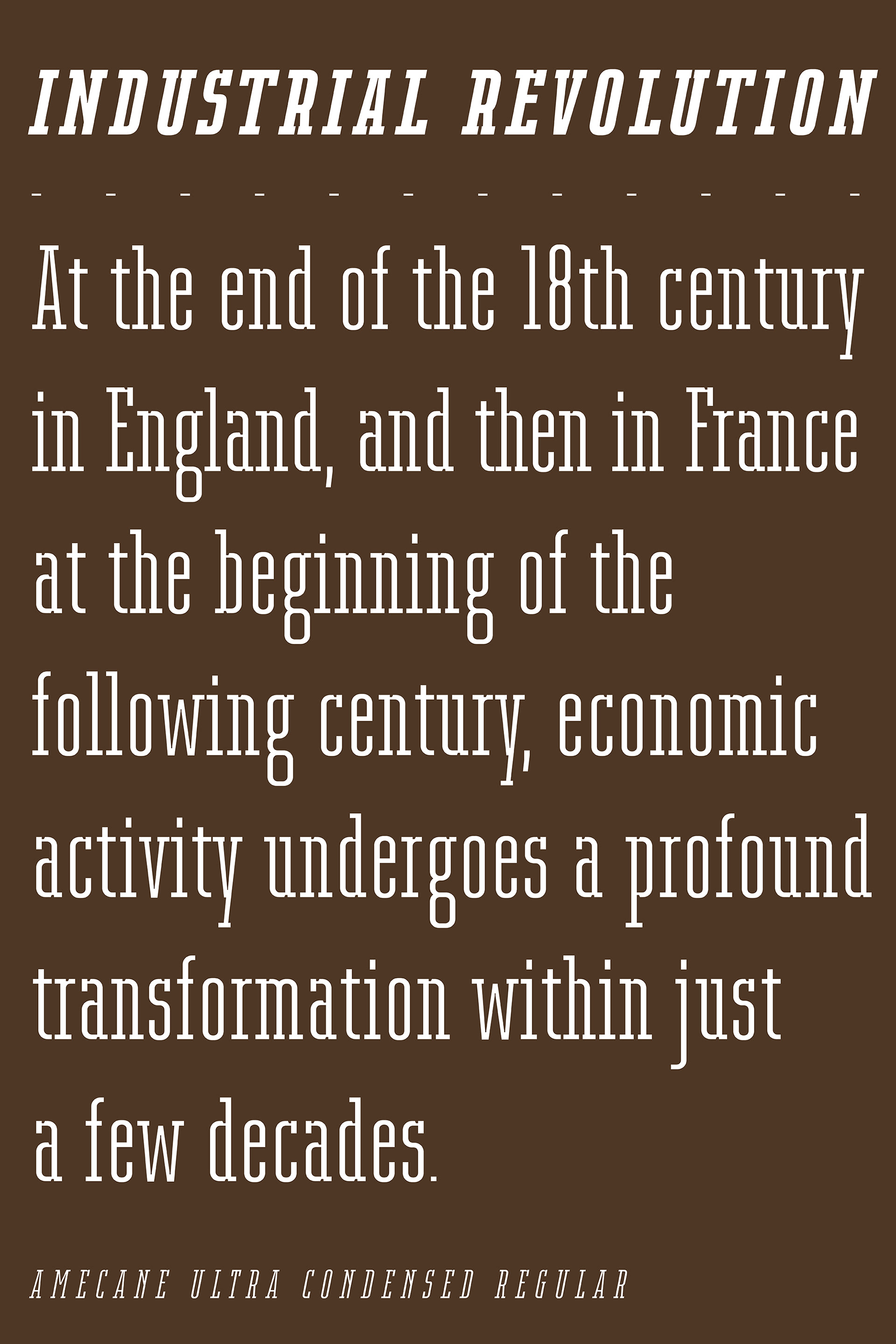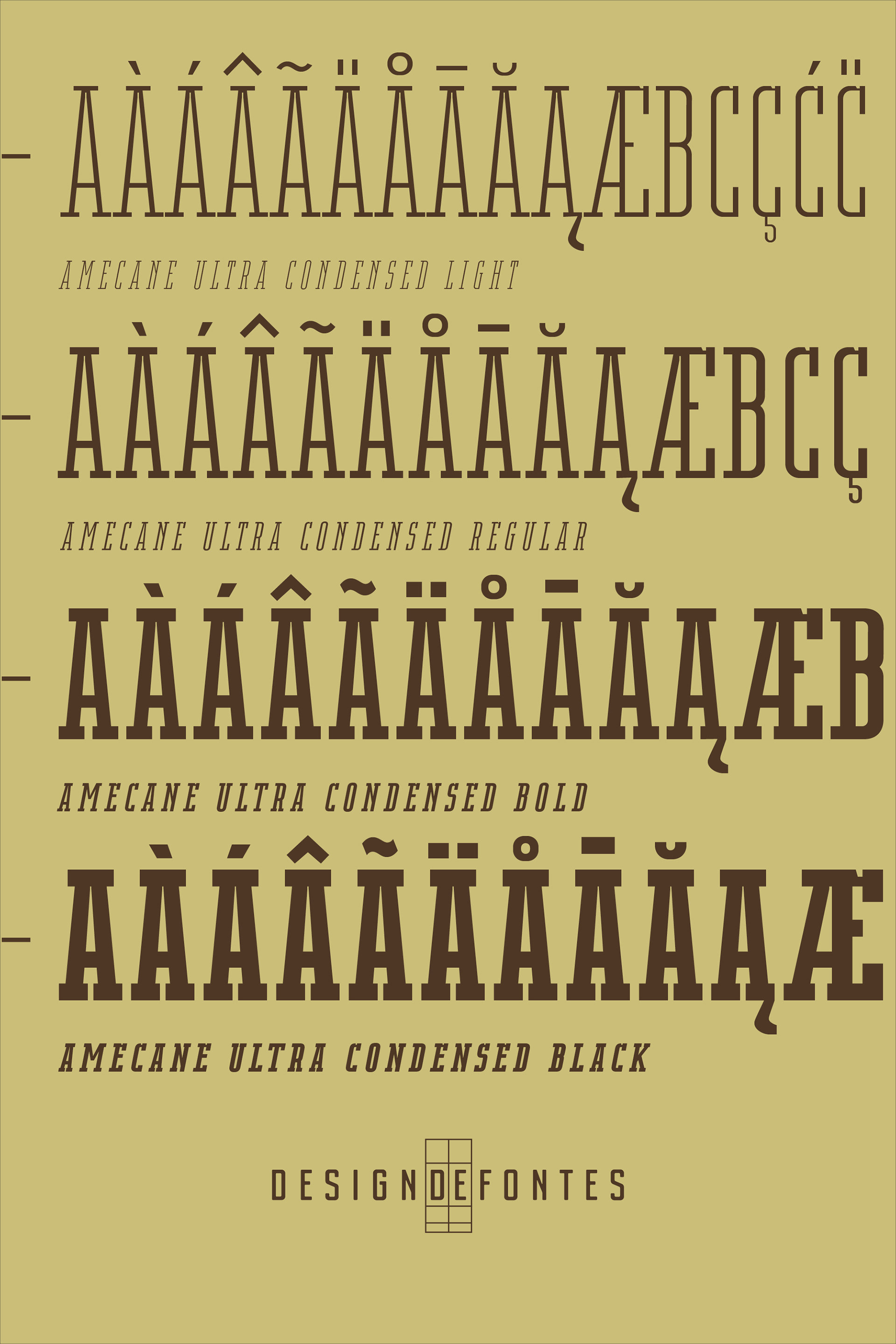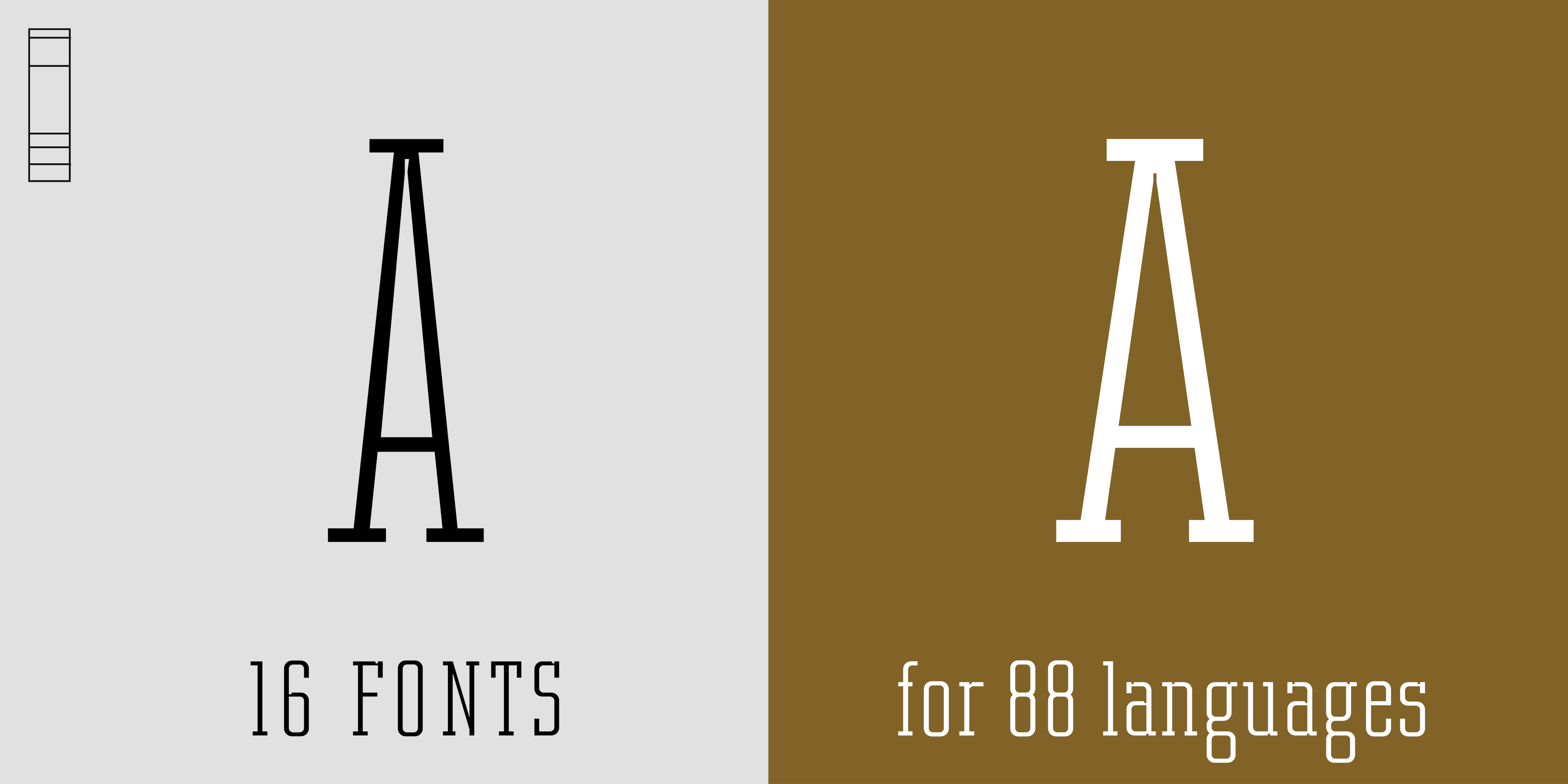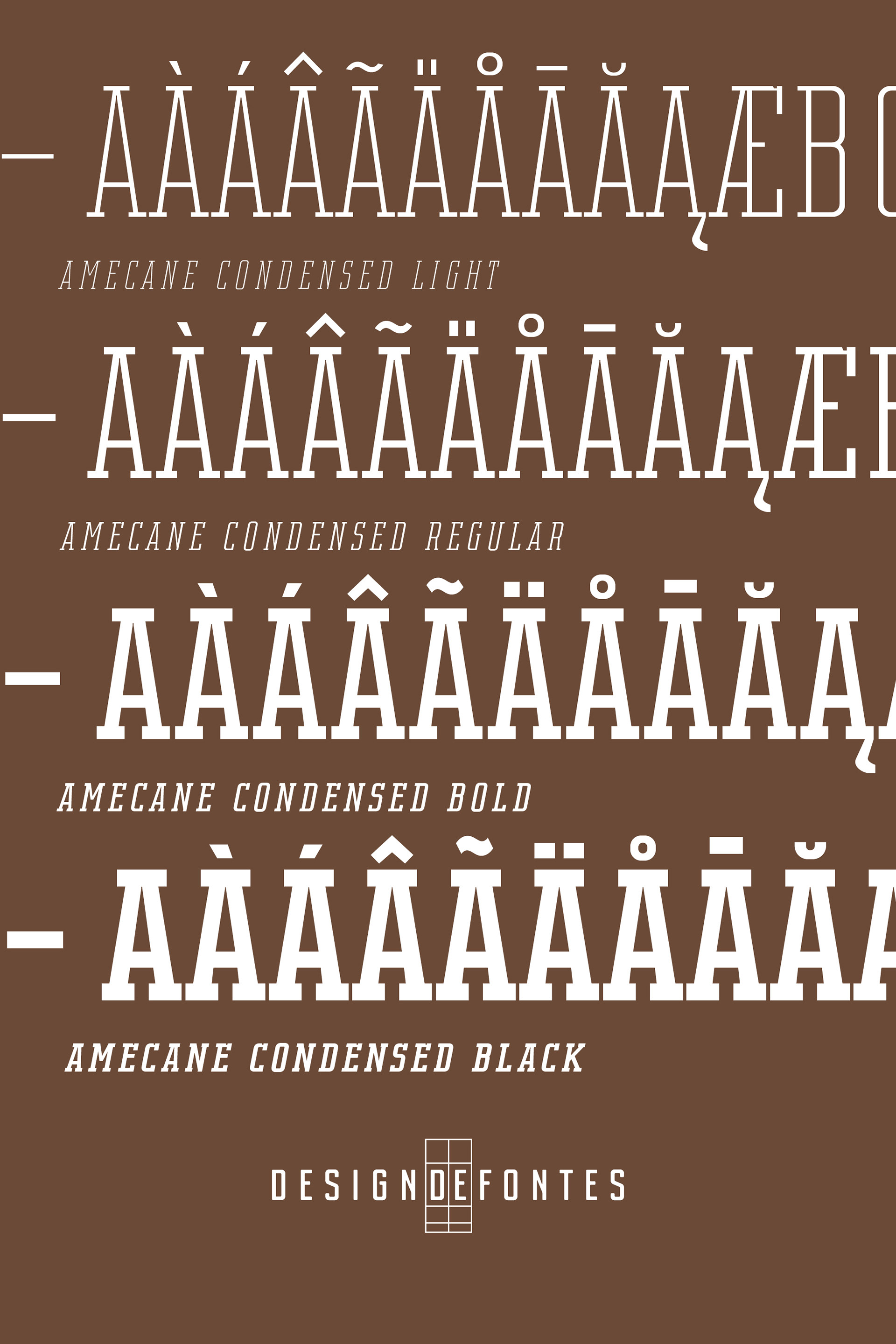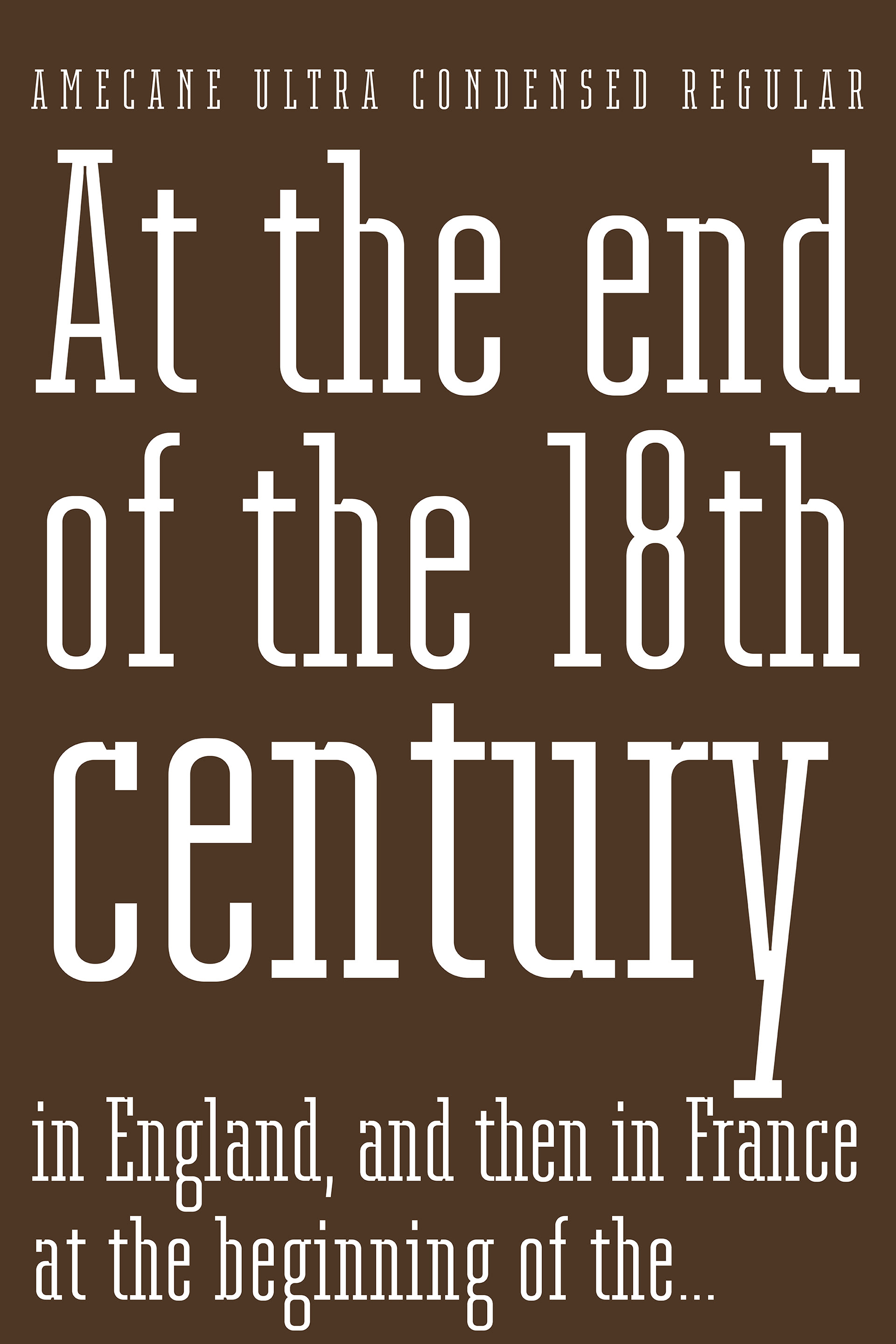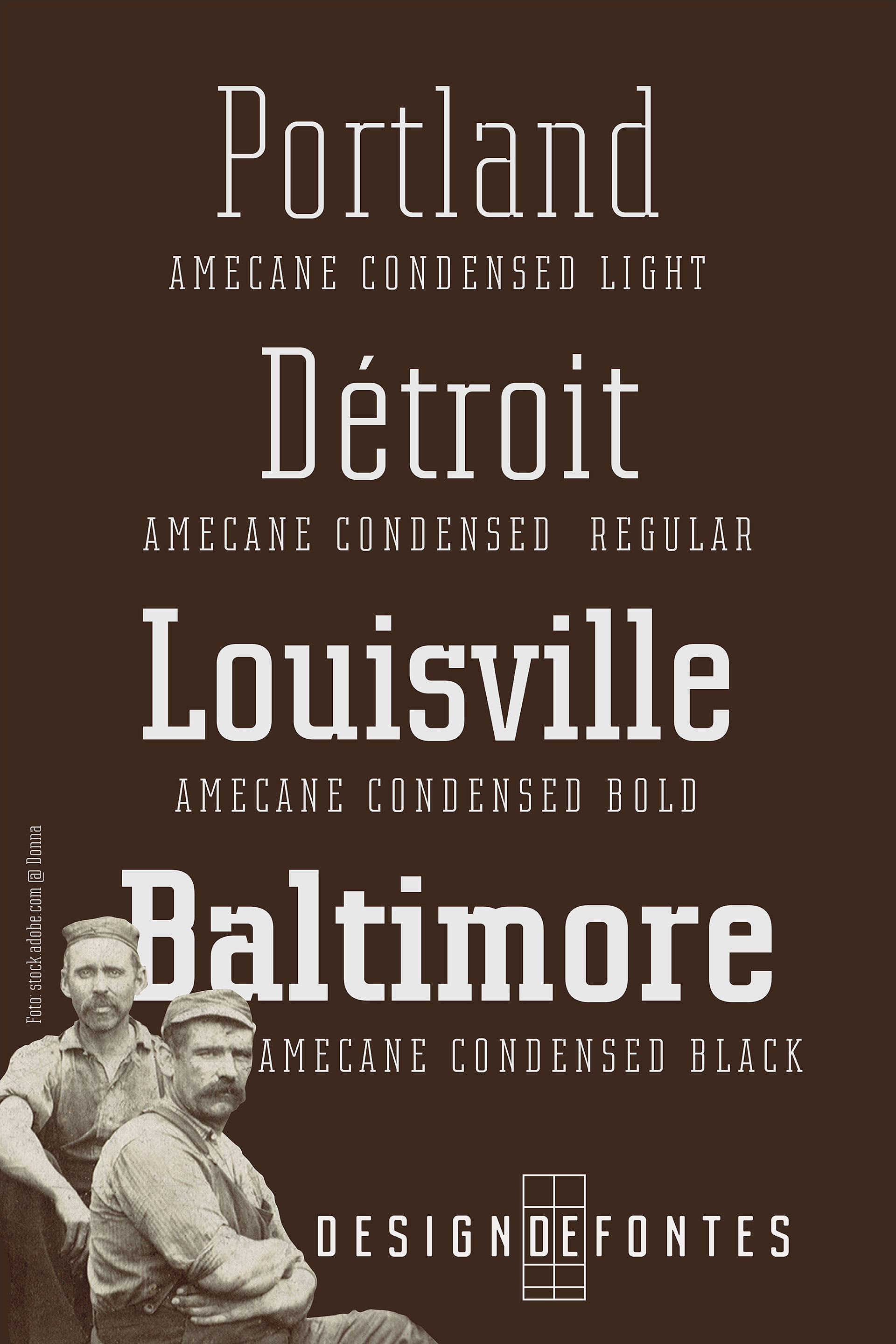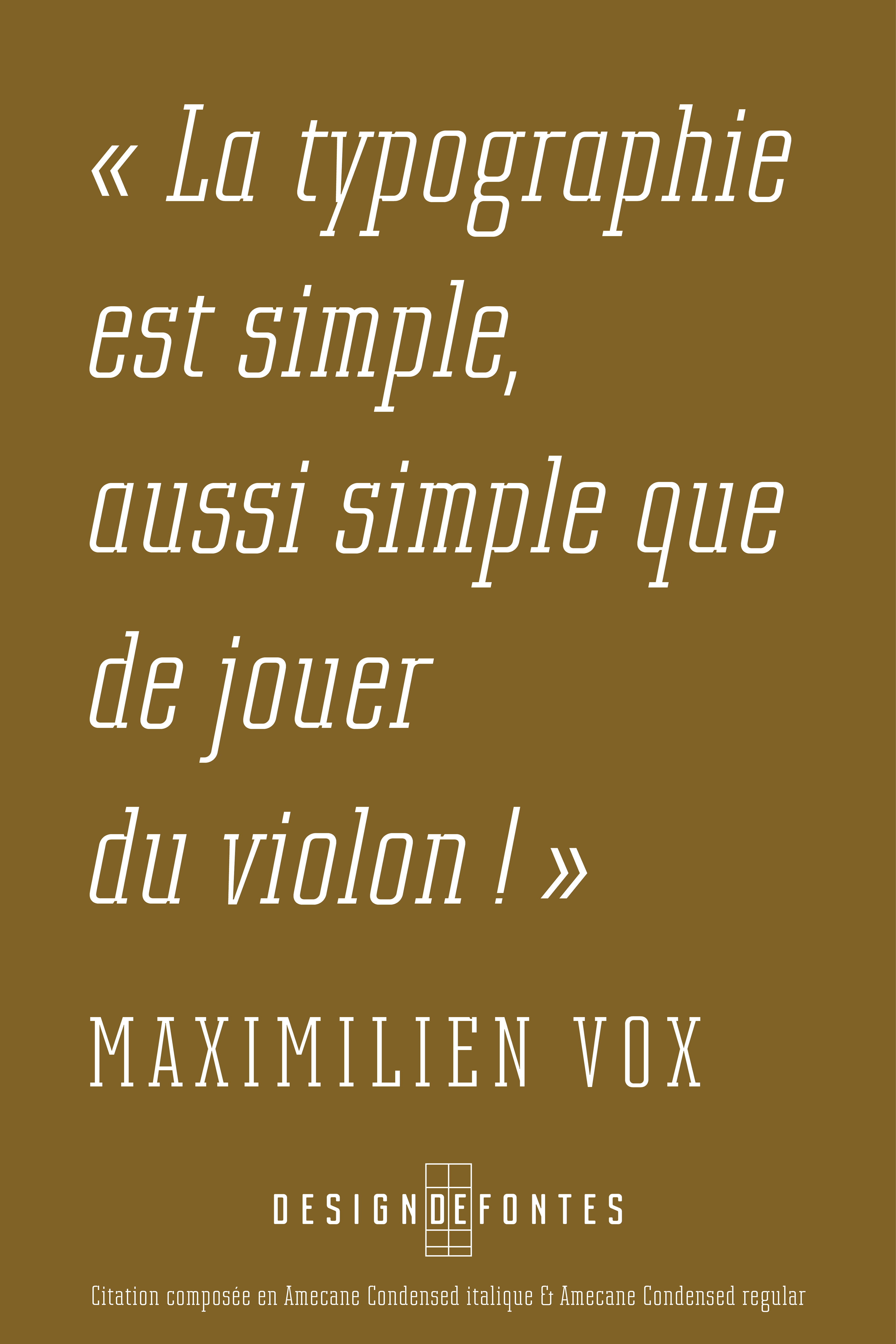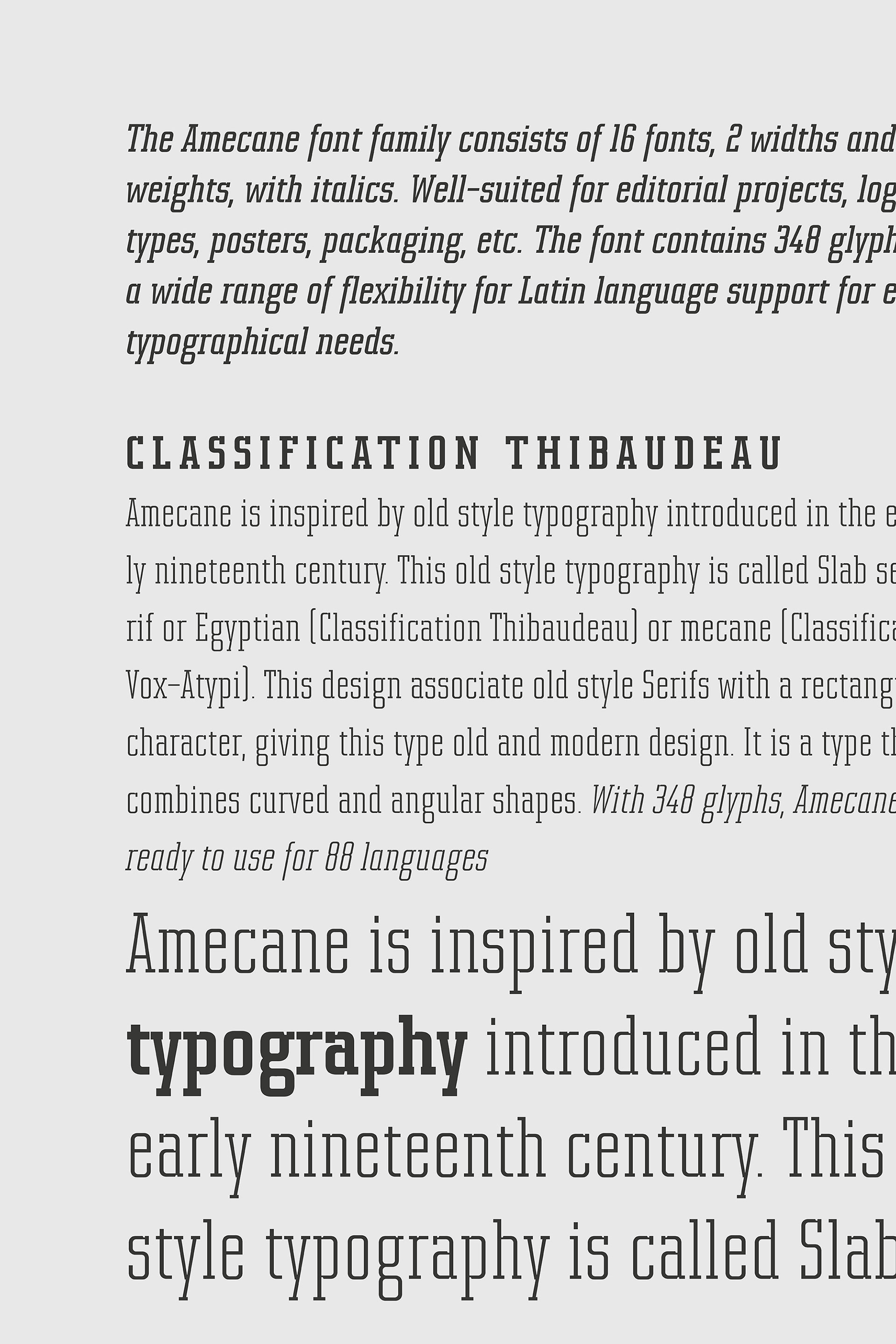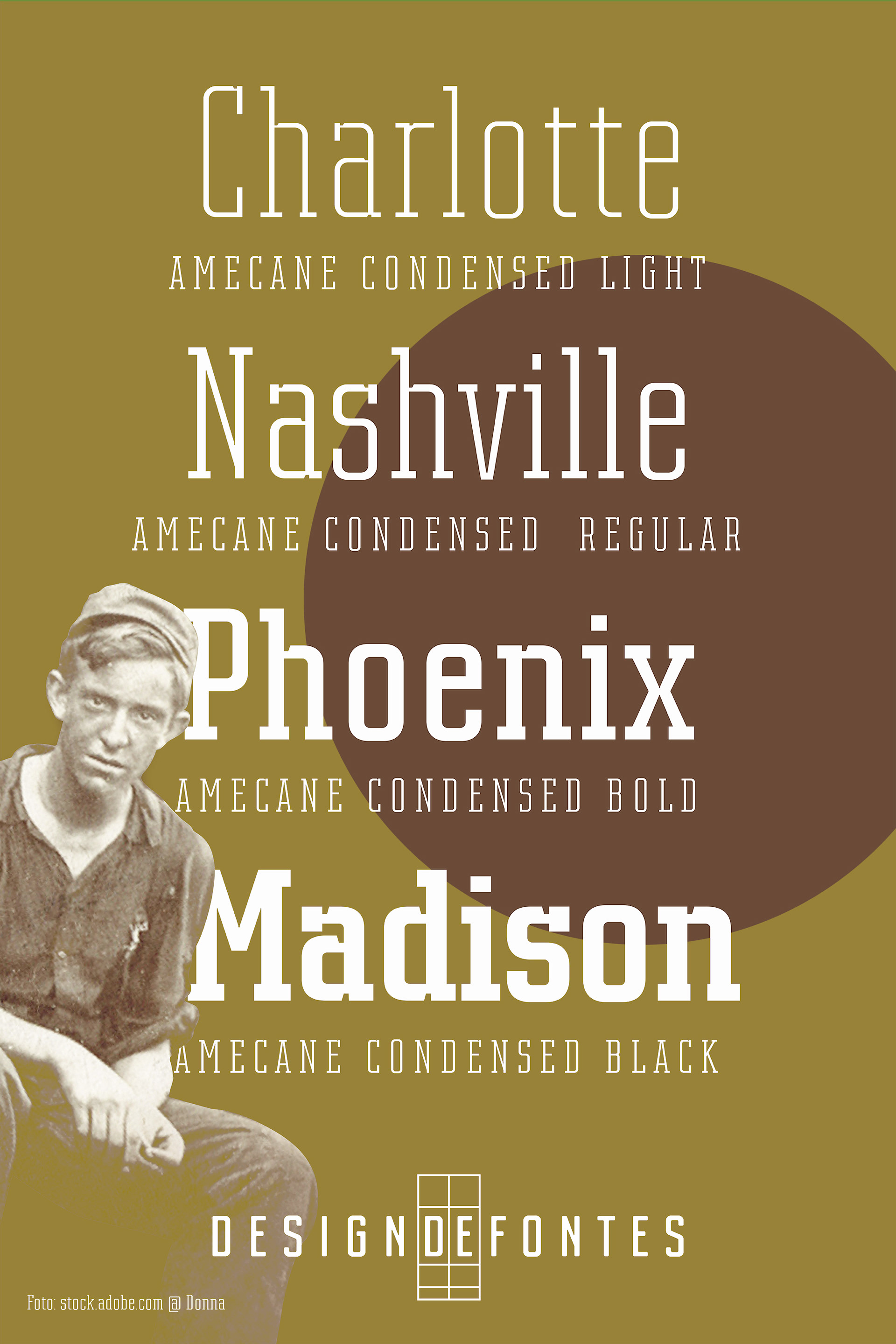
CARACTèRE TYPOGRAPHIQUE AMECANE
SCHRIFT AMECANE
Amecane est une mécane (a mecane) - dont le design a été réalisé par Loïc Choquet. Cette police comprend 16 fontes, 2 chasses et 8 graisses, ainsi que des italiques. Convenant à l’élaboration de projets éditoriaux, de logotypes, de posters, de packaging, etc. Ces fontes contiennent chacune 348 caractères offrant une large possibilité d’emploi pour toutes compositions en alphabet latin.
Amecane ist eine Slab-Serif-Schrift – entworfen von Loïc Choquet. Die Amecane-Schriftfamilie umfasst 16 Schriftarten, 2 Weiten und 8 Strichstärken, jeweils mit Kursivvarianten. Sie eignet sich hervorragend für Editorial-Designs, Logos, Plakate, Verpackungen und mehr. Die Schrift enthält 348 Glyphen und bietet eine hohe Flexibilität für die Unterstützung lateinischer Sprachen, um sämtlichen typografischen Anforderungen gerecht zu werden.
Amecane est un caractère inspiré par d’anciens caractères typographiques qui ont été développés au début du XIXe siècle. Ces caractères ont été classés sous le nom d’égyptiennes (Classification Thibaudeau) ou de mécanes (Classification Vox-Atypi). Le design d’Amecane associe des empattements rectangulaires spécifiques à un design global inscrit dans des formes rectangulaires, associant ainsi un style retro dans des gabarits plus modernes. C’est un caractère qui associe des lignes courbes et des formes anguleuses.
Amecane ist eine von alten Schriften inspirierte Schrift, die Anfang des 19. Jahrhunderts entwickelt wurden. Diese Schriften wurden als Égyptiennes (nach der Thibaudeau-Klassifikation) oder Mécanes (nach der Vox-Atypi-Klassifikation) eingeordnet. Das Design von Amecane kombiniert charakteristische rechteckige Serifen mit einer insgesamt rechteckigen Formgebung. Dadurch verbindet sie einen Retro-Stil mit moderneren Proportionen. Die Schrift vereint geschwungene Linien mit kantigen Formen.
Grâce à ses 348 glyphes Amecane est utilisable pour 88 langues.
Dank ihrer 348 Glyphen ist Amecane für 88 Sprachen einsetzbar.
16 fontes
Ultra Condensed Light, Ultra Condensed Light Italic, Ultra Condensed, Ultra Condensed Italic, Ultra Condensed Bold, Ultra Condensed Bold Italic, Ultra Condensed Black, and Ultra Condensed Black Italic.
Condensed Light, Condensed Light Italic, Condensed, Condensed Italic, Condensed Bold, Condensed Bold Italic, Condensed Black, and Condensed Black Italic.
Strichstärken & Stile (16 Schnitte)
Ultra Condensed Light, Ultra Condensed Light Italic, Ultra Condensed, Ultra Condensed Italic, Ultra Condensed Bold, Ultra Condensed Bold Italic, Ultra Condensed Black, and Ultra Condensed Black Italic.
Condensed Light, Condensed Light Italic, Condensed, Condensed Italic, Condensed Bold, Condensed Bold Italic, Condensed Black, and Condensed Black Italic.